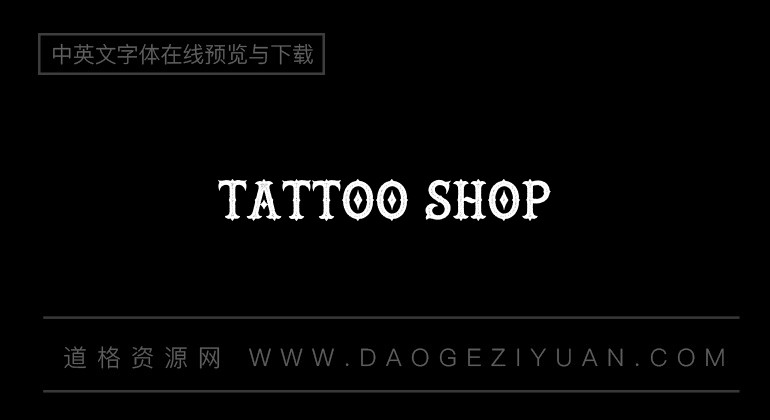
Tattoo Shop 字体是一款拥有独特、鲜明、灵活的设计风格的字体,它专为刺青设计,适合创作出各种性格鲜明的刺青作品。Tattoo Shop 字体具有非常独特的书写体,其中不仅包含了一些传统的梯形字体,还有一些非常新颖的设计,能够让你的刺青作品更加丰富、独特。此外,Tattoo Shop 字体还有一个特点就是它的字体大小很容易调整,可以让你根据自己的需要调整字体大小,从而更加容易地完成刺青作品。内容介绍
Tattoo Shop是一款非常不错的手写艺术字体,具有很好的视觉感,适合于文化类的宣传设计、商业类品牌的广告和产品包装设计以及个性化文字排版等较多场景。